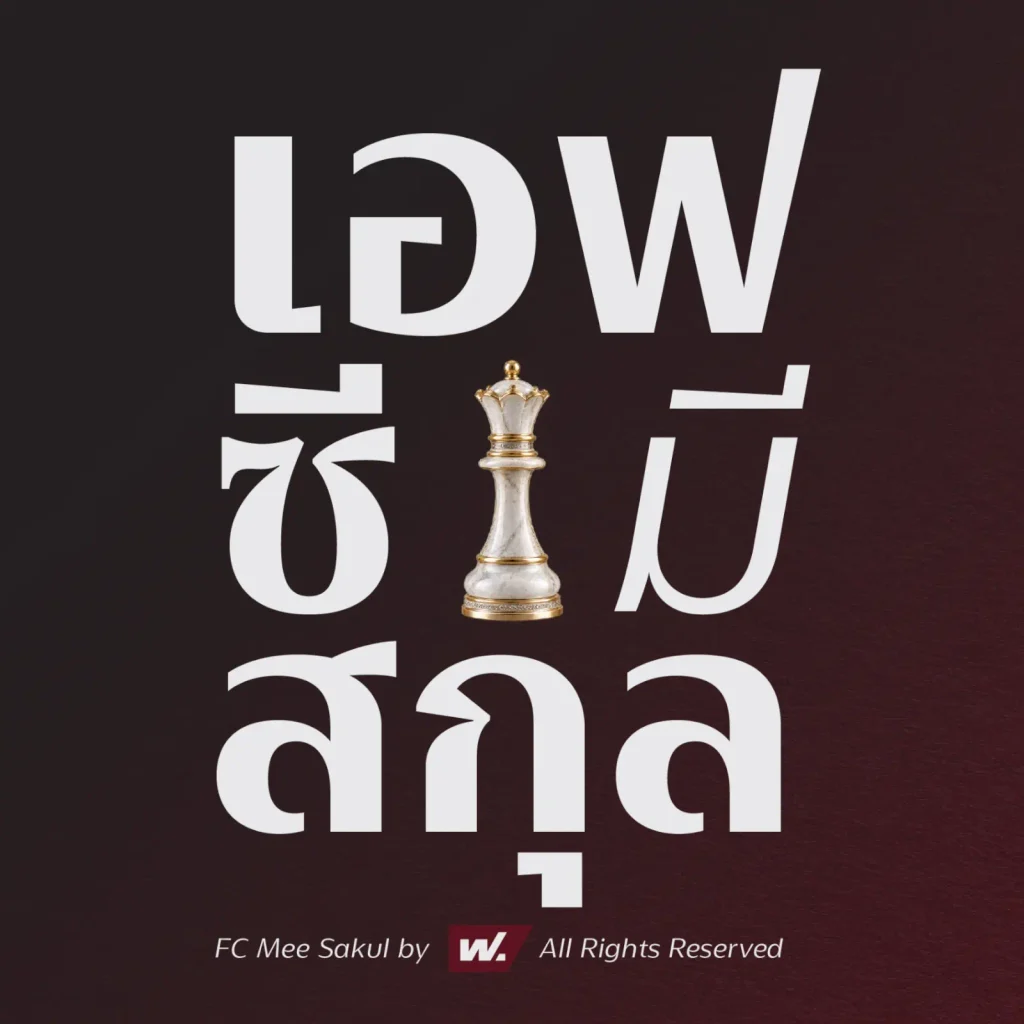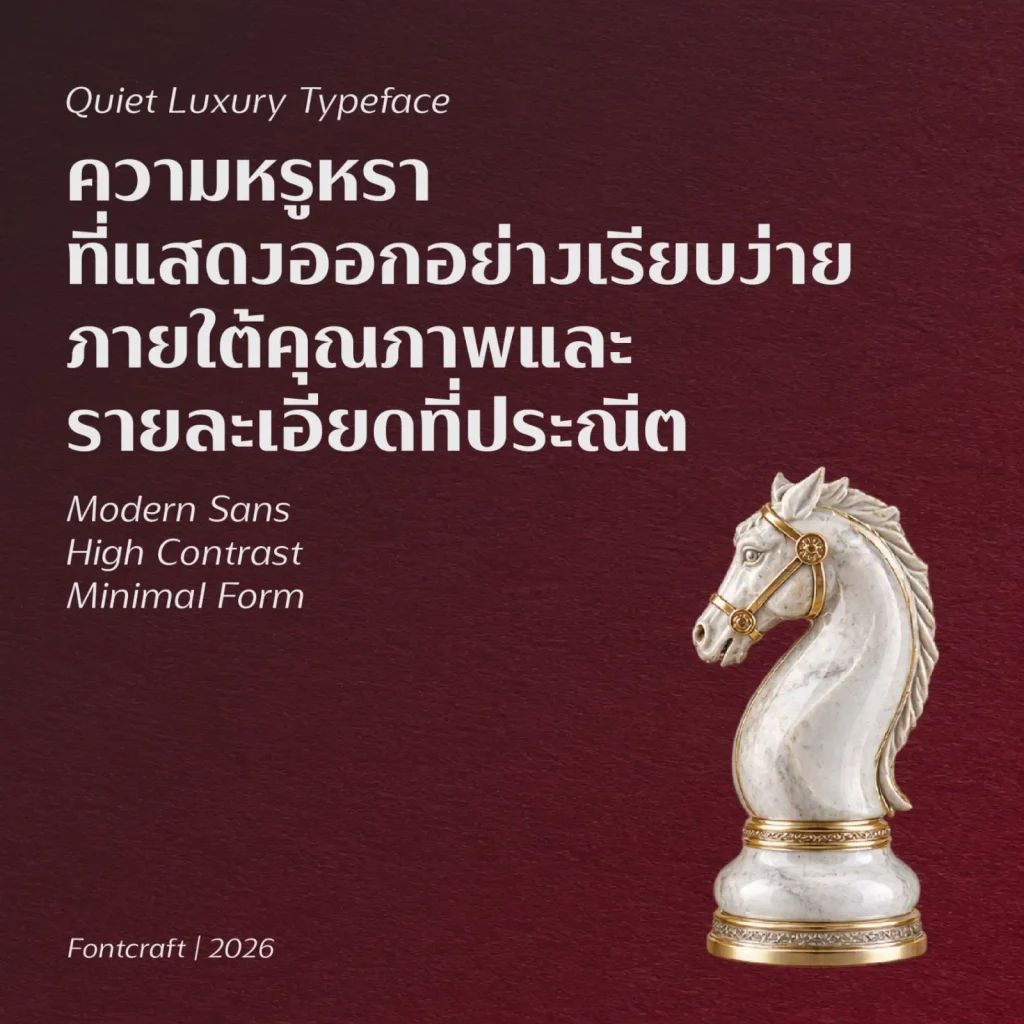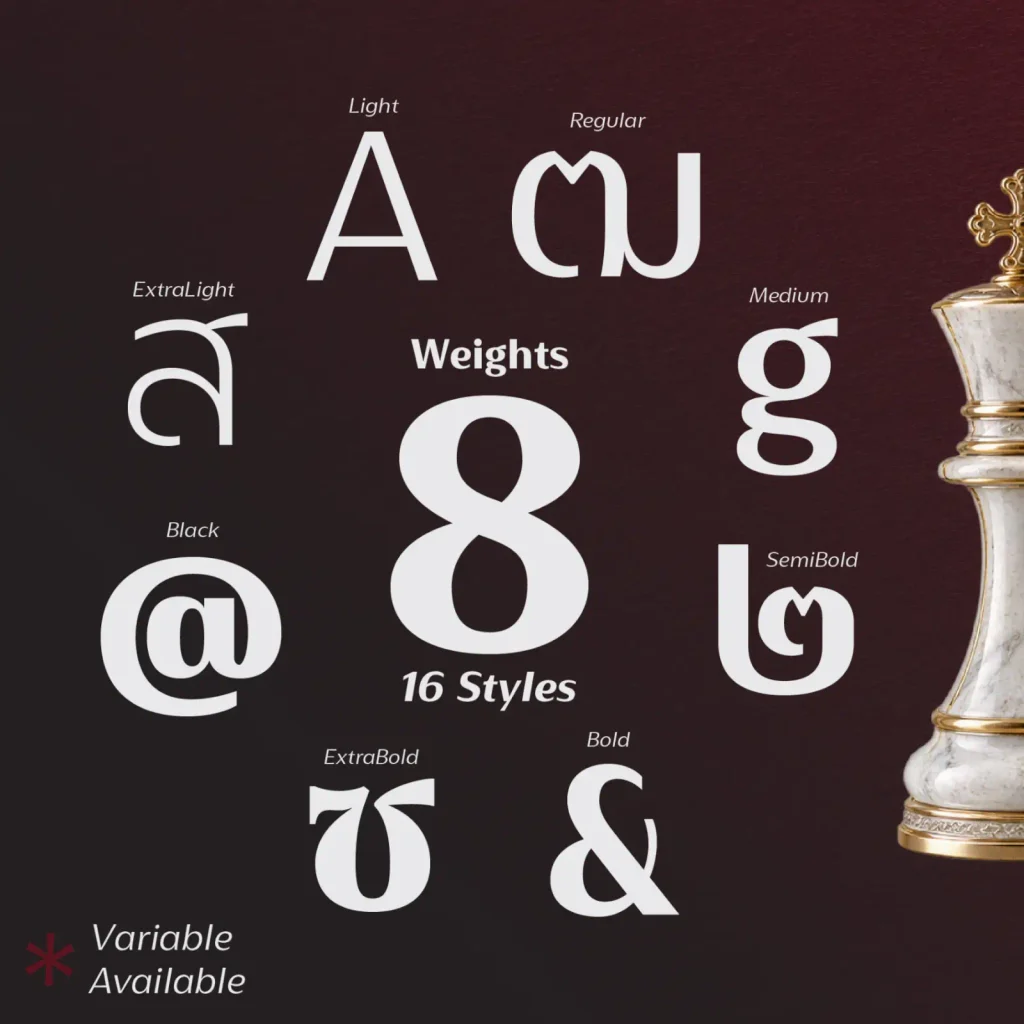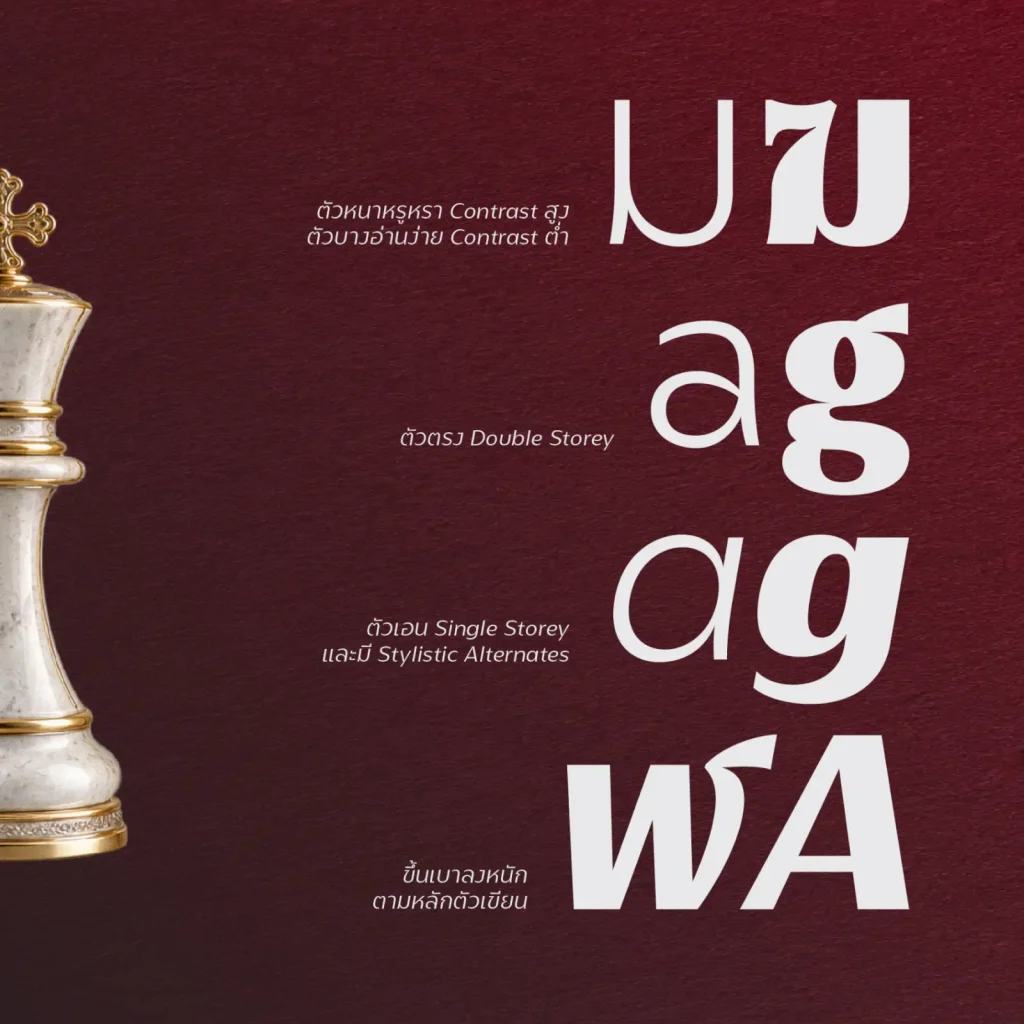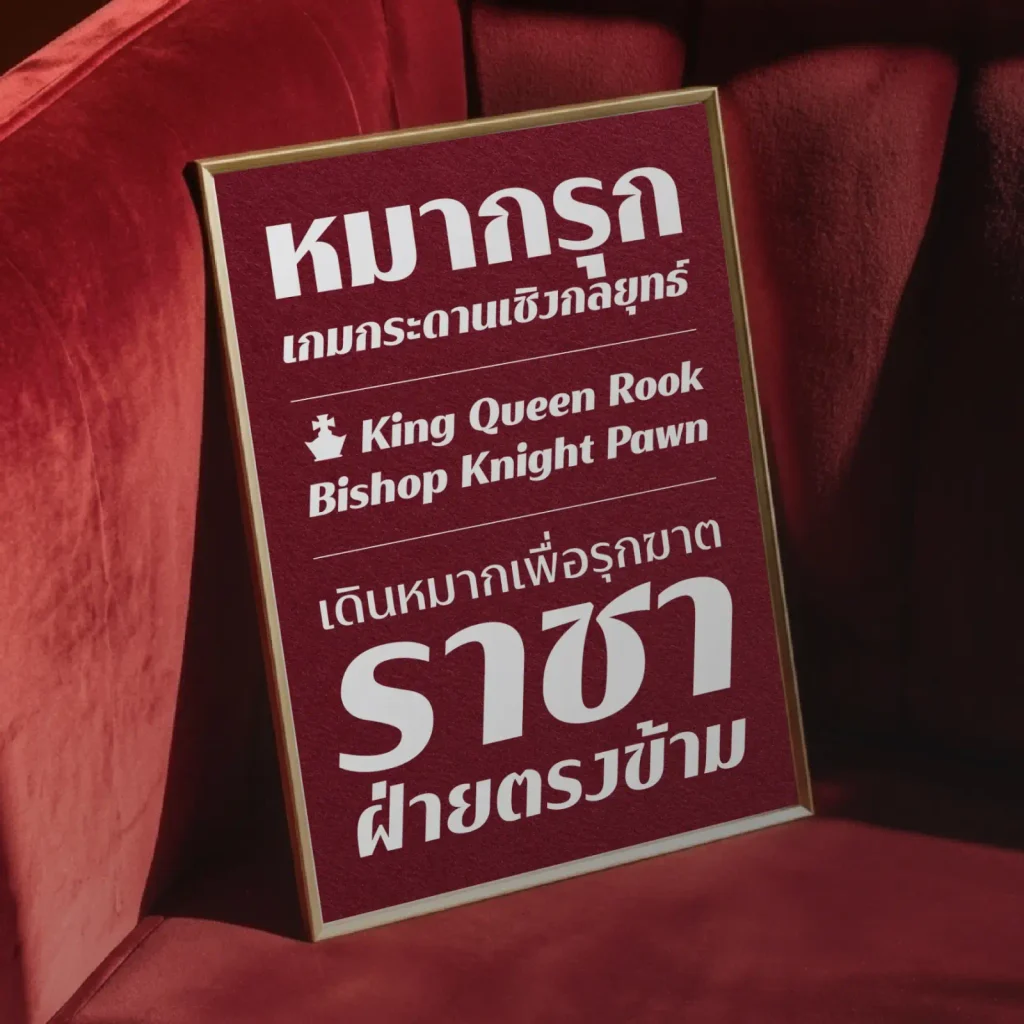
เอฟซี มีสกุล (FC Mee Sakul)
Quiet Luxury Typeface – ความหรูหราที่แสดงออกอย่างเรียบง่าย ภายใต้คุณภาพและรายละเอียดที่ประณีต
เพิ่มความสุขุม ผู้ดีมีเกียรติ และทรงพลังให้กับชิ้นงาน เลี่ยงการแสดงความหรูหราแบบตะโกนผ่านโครงสร้างสลับซับซ้อนของตัวอักษร เปลี่ยนเป็นโครงสร้างที่สะอาดตา น้ำหนักเส้นมี Contrast อย่างตั้งใจ
ตัวหนาหรูหรา เน้น Contrast ระหว่างเส้นตั้งและเส้นนอนให้เด่นชัด และตัวบางลด Contrast ให้ต่ำลงเพื่อให้อ่านได้ง่าย เส้นไม่จางหายไปเมื่อถูกใช้ในขนาดเล็ก รวมถึงมีการเปลี่ยนรูปแบบตัวอักษร a g จาก Double Storey เป็น Single Storey ในตัวเอน
มาพร้อม 8 ระดับความกว้างและตัวเอนรวม 16 สไตล์ มี Variable Font แยกจากชุดปกติ